Top 10 Font Việt Hóa Designer Nào Cũng Nên Có Nhất 2021
Font chữ việt hóa đẹp là tài nguyên mà nhiều cá nhân hoạt động trong lĩnh vực nghệ thuật, thiết kế quan tâm và tìm kiếm để tạo nên các sản phẩm sáng tạo cho riêng mình. Trong Designer, vai trò của font chữ việt hóa trong các thiết kế quảng cáo, banner cực kì quan trọng và với nhiều dự án thiết kế lớn nhỏ, nó có thể tác động đến nhận thức khách hàng và quyết định mua hàng của họ trong các khoảnh khắc đầu khi vừa đọc mẫu quảng cáo.
Top 10 Font Việt Hóa Designer Nào Cũng Nên Có Nhất 2021
Font Modern Society
Một font allcaps được vẽ tay với phong cách độc đáo. Với 2 kiểu in hoa và in thường khác nhau, trong đó bộ chữ hoa các ký tự nhấp nhô cao thấp tạo sự năng động và tươi mới. Modern Society thích hợp cho các thiết kế đầy sáng tạo, tinh nghịch, cute... được Việt Hóa bởi đội ngũ STYLEno.1 Fonts
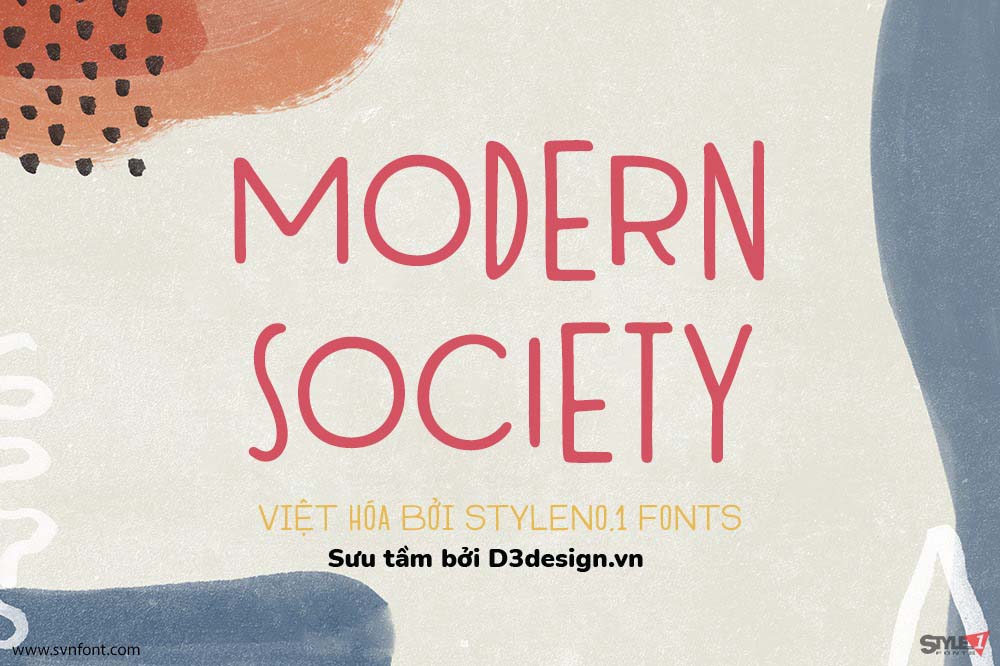
Font Saint Monica
Một font chữ linh hoạt, hiện đại và thanh lịch. Font phù hợp cho thiết kế logo, biểu trưng, tạp chí, tiêu đề... được Việt Hóa bởi đội ngũ STYLEno.1 Fonts
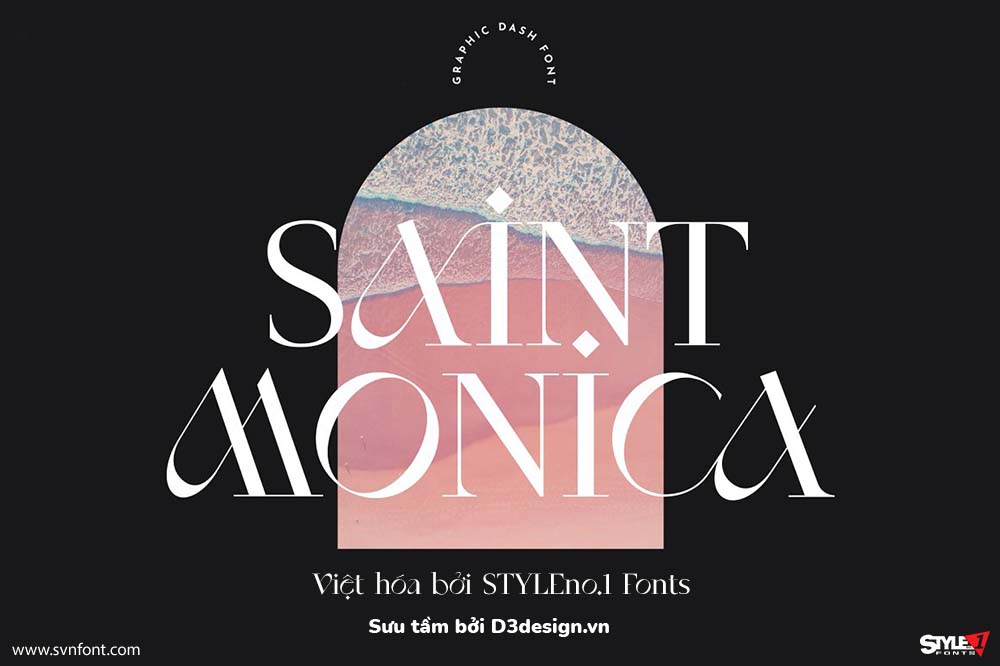
Font Sage
Một serif font hiện đại và đa phong cách. Một phiên bản tương phản cao của Didot nổi tiếng đã đồng hành cùng ngành thời trang trong nhiều thập kỷ. Với độ tương phản cao, font chỉ thích hợp cho tiêu đề, biểu trưng, text size lớn, ở size nhỏ sẽ gây khó đọc. Kết hợp với font sans hoặc script nhẹ sẽ đẹp hơn. Được Việt Hóa bởi đội ngũ STYLEno.1 Fonts
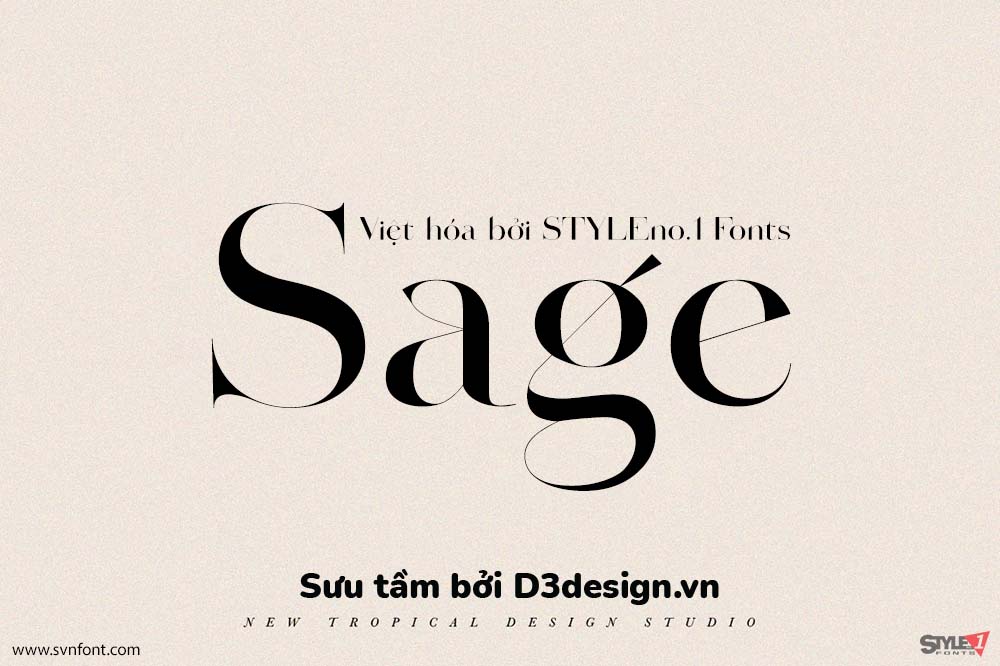
Font Stradas
Một display font "đáng kinh ngạc", font rất đẹp và sang trọng, thích hợp cho mọi dự án như thương hiệu, typo, logo, nhãn hiệu... được Việt Hóa bởi đội ngũ STYLEno.1 Fonts
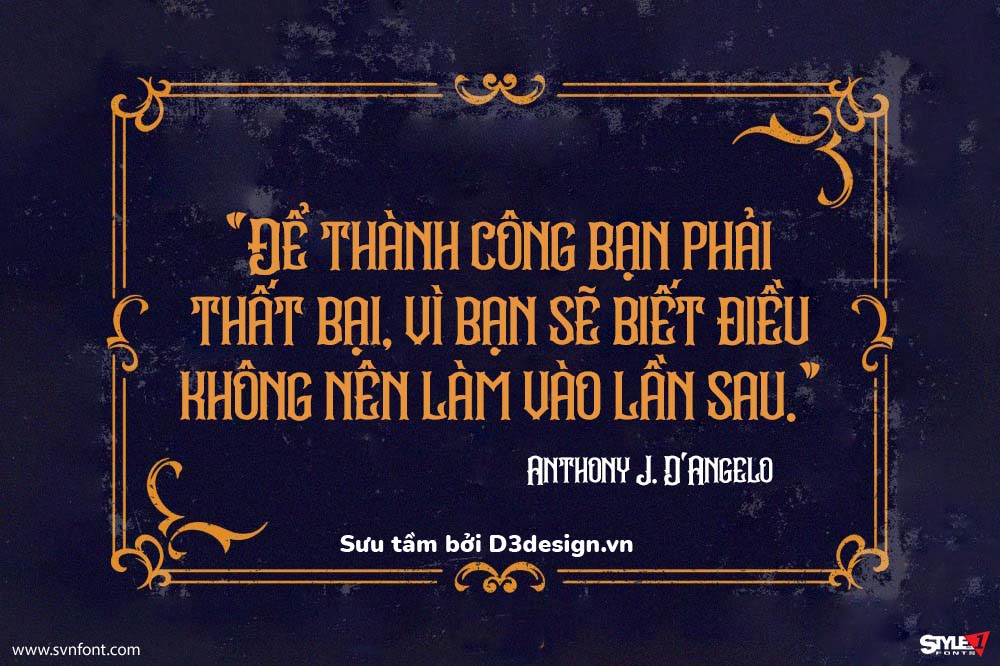
Font Mercuria
Một font đậm mạnh mẽ, nguyên bản, gợn sóng và thân thiện. Với dự độc đáo và phong cách của nó, font phù hợp với nhiều thiết kế: tiêu đề, sản phẩm, nhãn hiệu, bao bì... được Việt Hóa bởi đội ngũ STYLEno.1
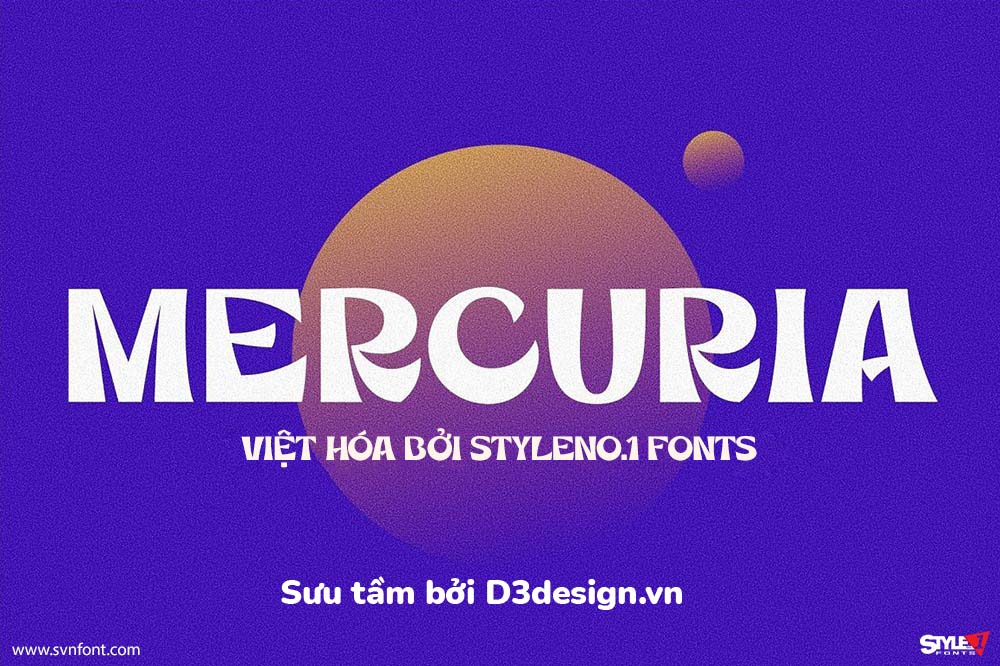
Font Gallery Modern
Một font chữ hiện đại và rất đặc trưng bởi các nét chữ của nó. Các đường cong "nuột nà" đầy tinh tế tạo nên một font độc đáo. Font thích hợp cho các thiết kế về thời trang, thương hiệu, typography, nhiếp ảnh... được Việt Hóa bởi đội ngũ STYLEno.1
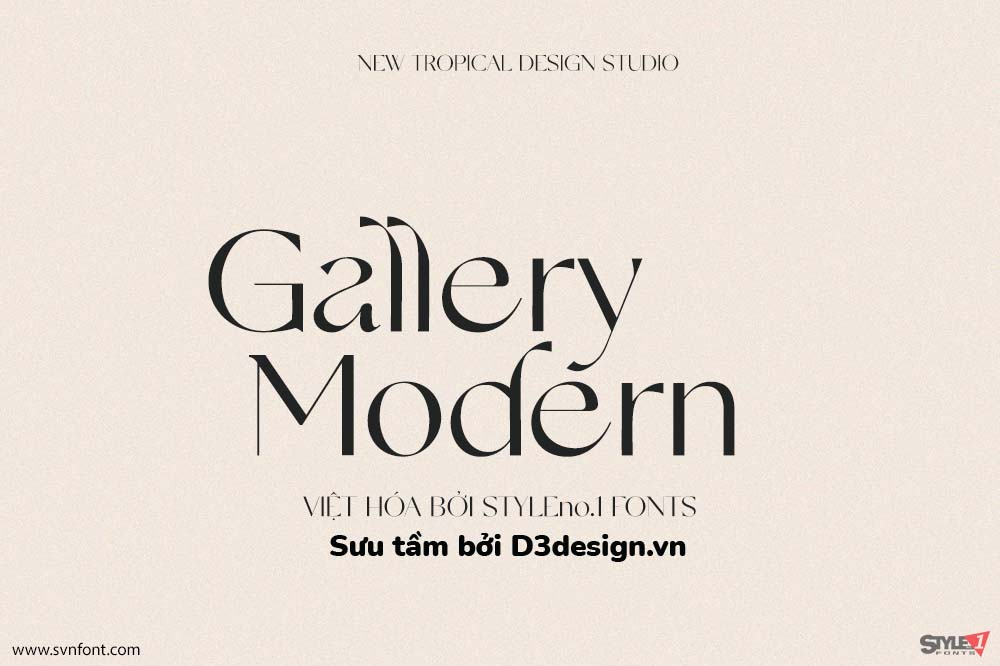
Font Consent
một typeface serif display với kiểu chữ in hoa. Font chữ có độ tương phản mạnh, tạo độ trang nhã và sang trọng. Font phù hợp với thiết kế về tiêu đề, tạp chí, thương hiệu, logo... Font có sự khác biệt vài chi tiết nhỏ khi gõ chữ hoa và chữ thường. Được Việt Hóa bởi đội ngũ STYLEno.1
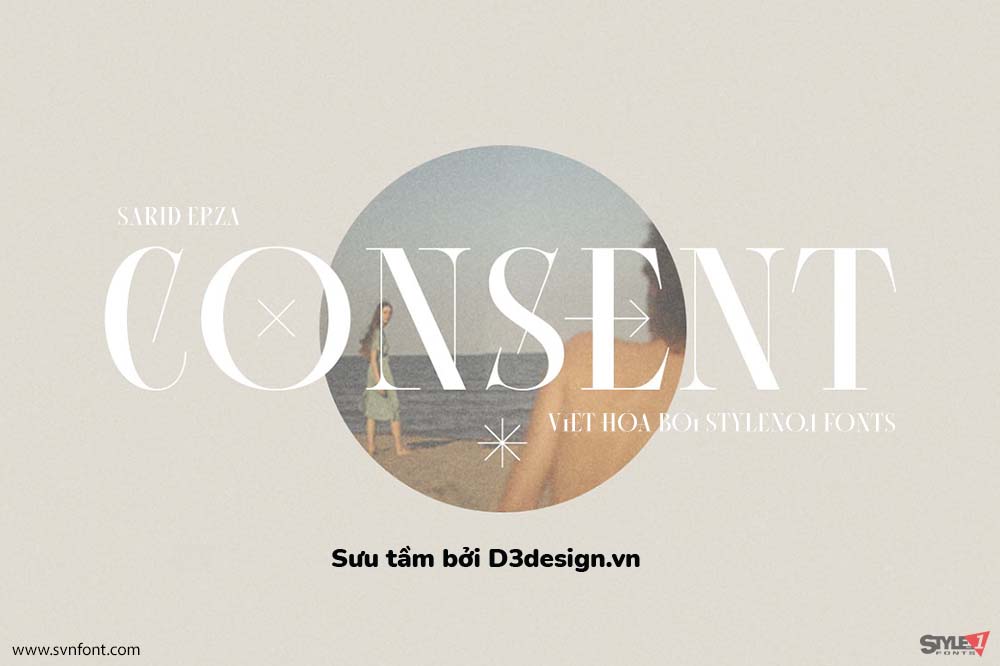
Font Sunflower
Một font serif hiện đại nhưng chứa nhiều yếu tố cổ điển. Font hoàn hảo cho nhiều dự án: thời trang, tạp chí, logo, thương hiệu, nhiếp ảnh, trích dẫn, tiêu đề... Được Việt Hóa bởi đội ngũ STYLEno.1
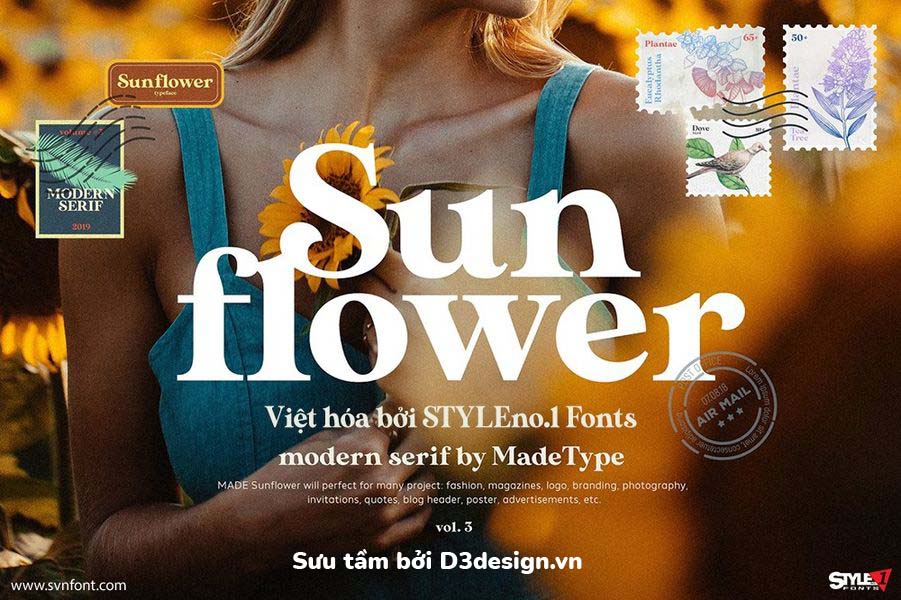
Font NewYork Typeface
Font chữ việt hóa - NewYork Typeface, Phông chữ được Việt hóa bởi March Nguyen
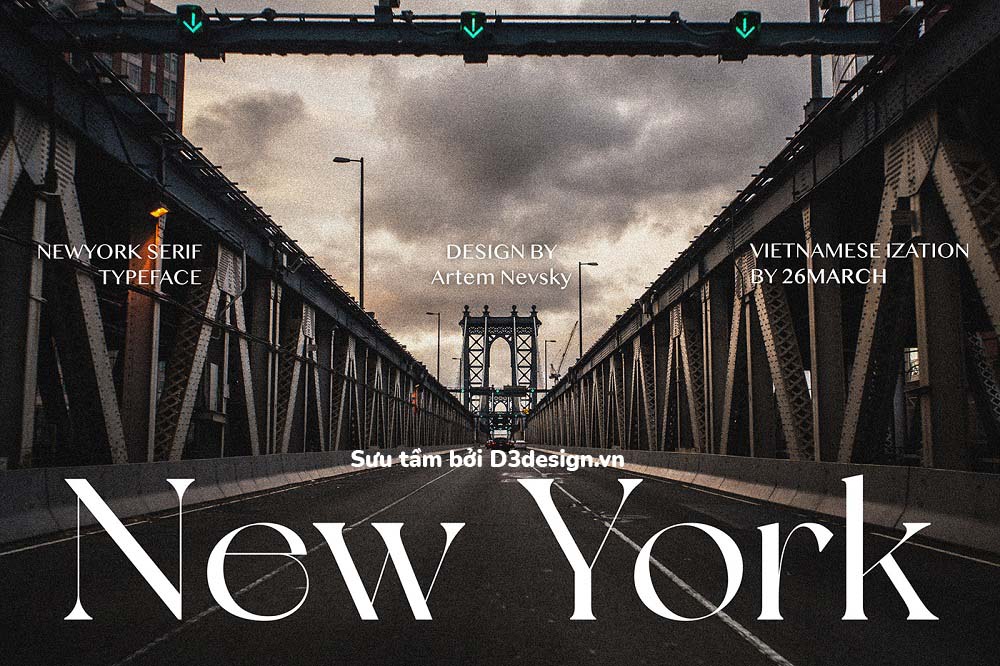
Font Caviar Dreams
Caviar Dreams là một font chữ đẹp mắt với cấu trúc chữ đơn giản và tinh tế. Đi kèm với sự phá cách hiện đại và đẹp mắt, dễ đọc.